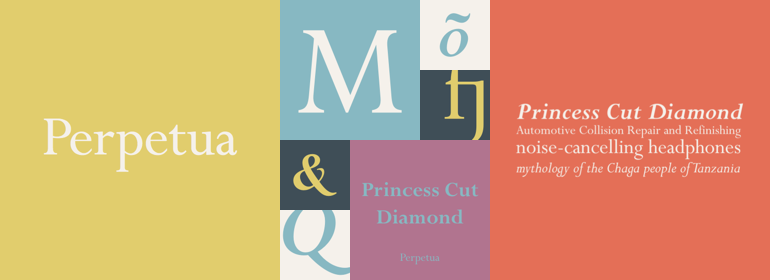
Perpetua®
20世纪早期,Eric Gill基于旧版画设计了Perpetua字体。这种字体使文本看起来有种正式的感觉,部分原因是由于它小小的衬线以及中世纪风格的数字。
Eric Gill designed Perpetua font in the early part of the 20th century, basing it on the designs of old engravings. The formal impression which this font lends to any text is due in part to its small, diagonal serifs and its medieval numbers.